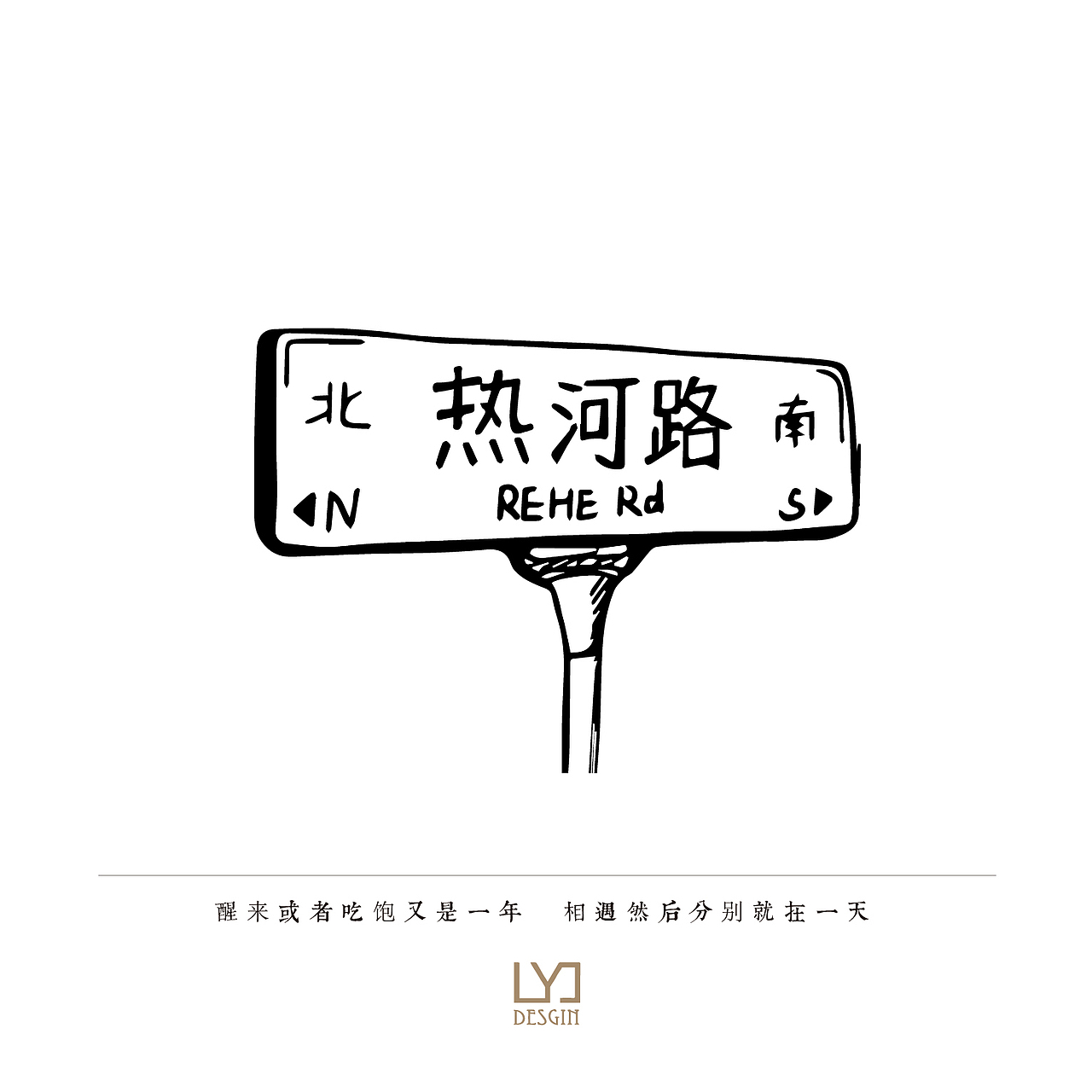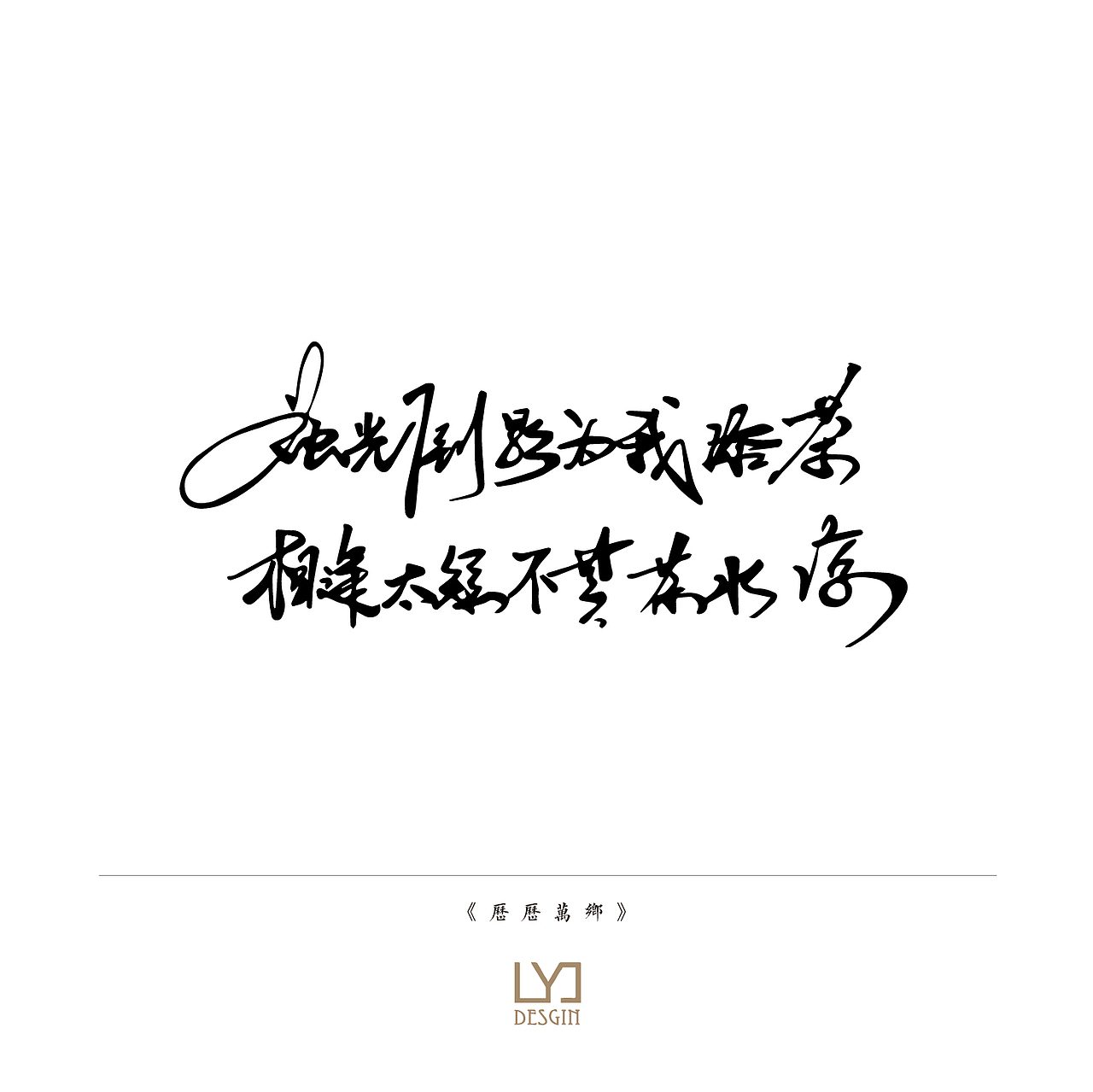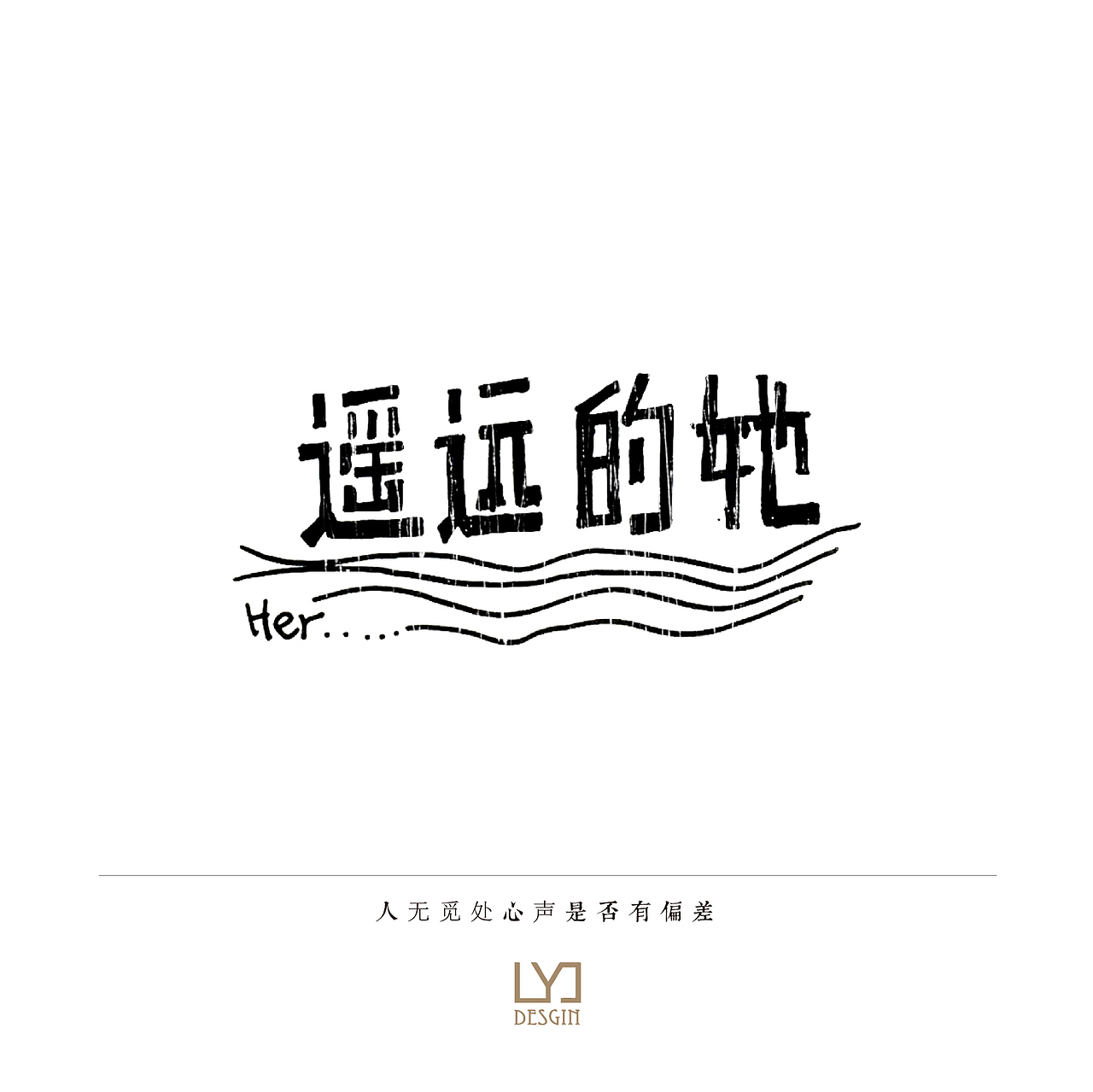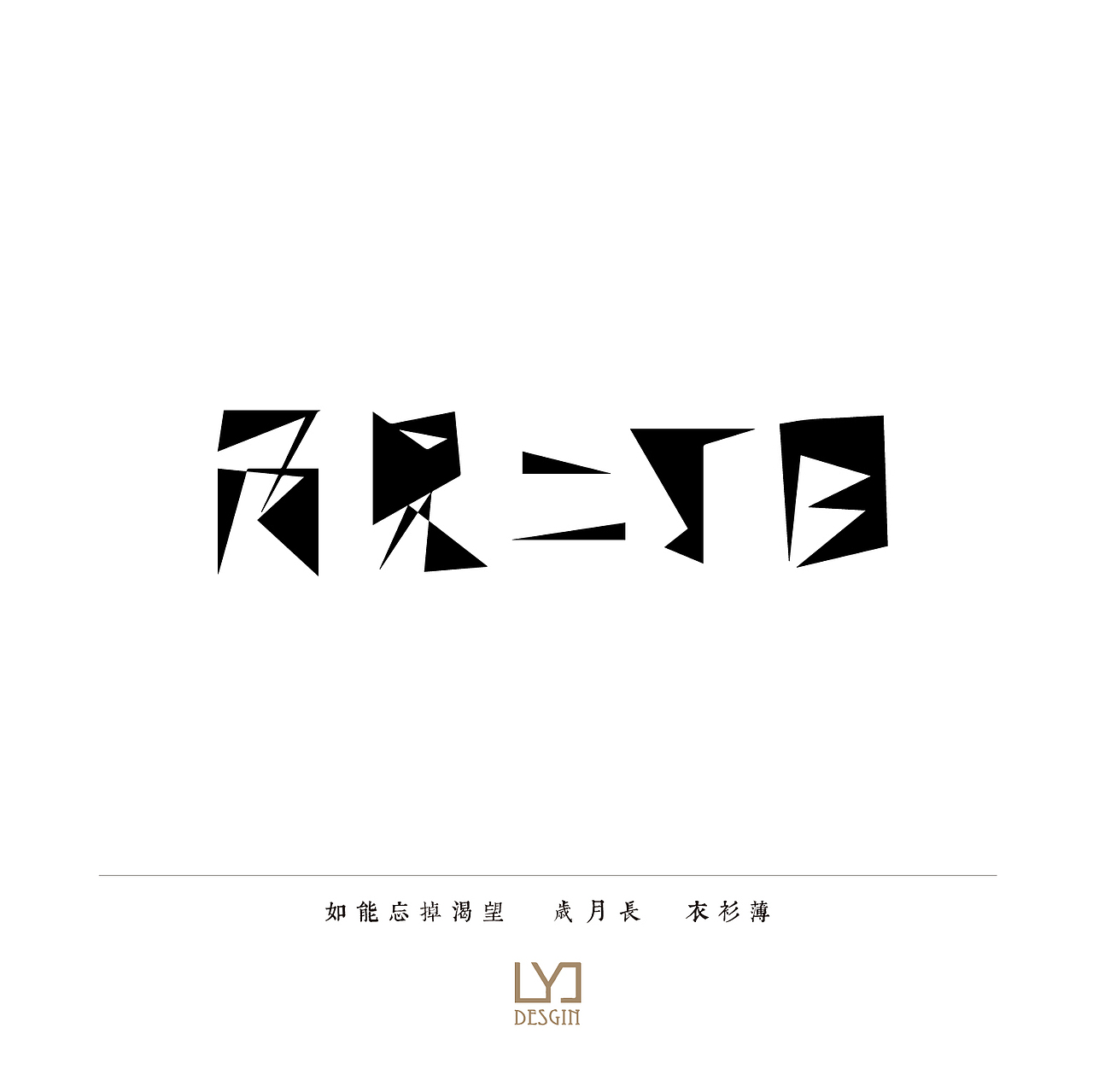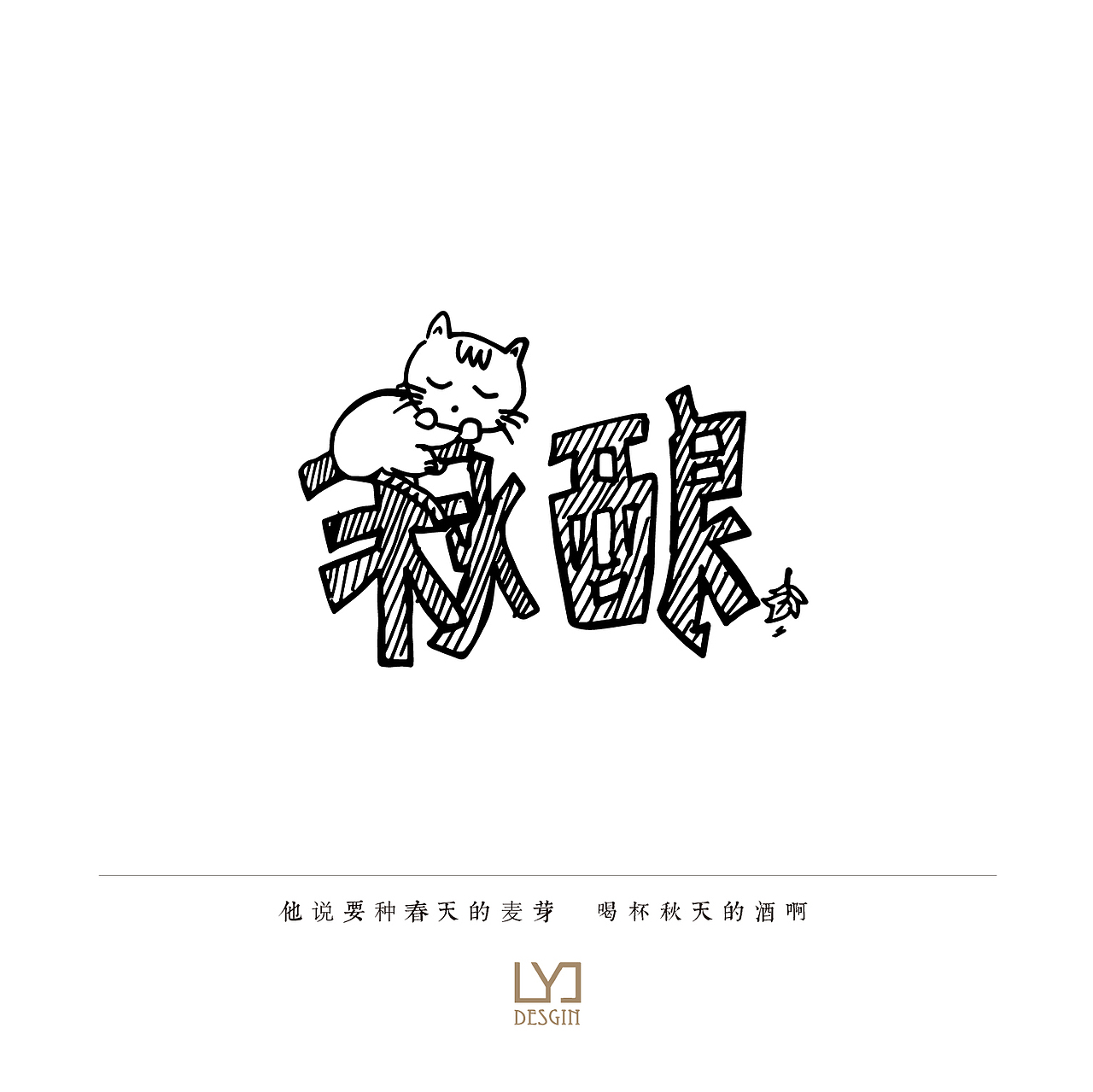
字练
遇到喜欢的歌,总想把他变成自己的方式表达出来,或是唱出来,或是画出来,都不行的话,那就写出来。不用形式感,冲击力,高大上,自己看着喜欢就行。没有要求的要求,是内心最真实的表达~
(内个,导出来的图片都是在手机上预览的笑尺寸,哈哈懒得改了,就这么随性?就这么随性!)
小时候家里有一盘崔健的磁带,花房姑娘那个感觉跟噪音似的,十几年过后,听崔健,诶?越来越好听了啊喂~
杨千嬅,我钟意你啊~
作为一个石家庄人,听到这个歌名,有种……算了,反正万能青年旅店也是庄里的,反正这个歌好听~
女人听了想嫁人,男人听了想女人!
他喜欢李志的歌曲,我喜欢他,我也喜欢他
我的小目标,几年能弹唱这首歌,像白若溪的五十分之一就行哈哈
学友大哥是ex最喜欢的歌手,这六七年,我只是偶尔听他~
陈粒歌好听,歌词也甚是好听。
野孩子乐队的声音浑厚,朴实,就是西北的感觉,黄河的感觉。土色的大地一样的感觉。不像现在很红的民谣们,听起来也很好听,但是容易腻,像奶油蛋糕,只能吃几口罢。